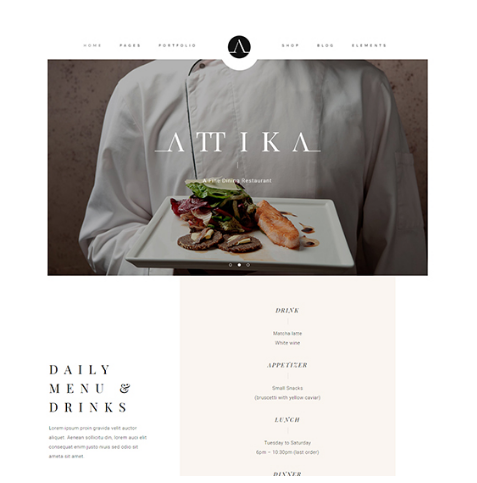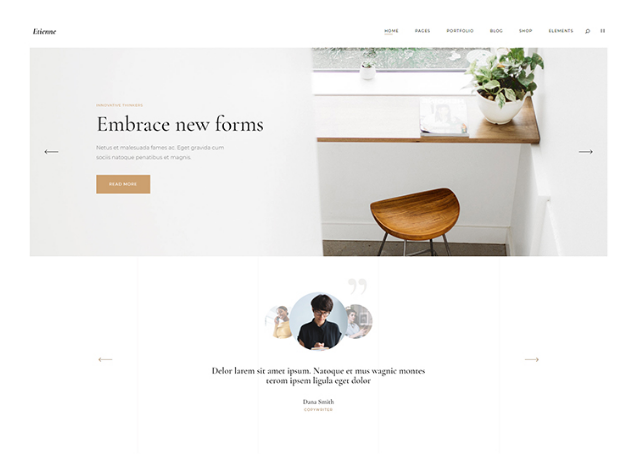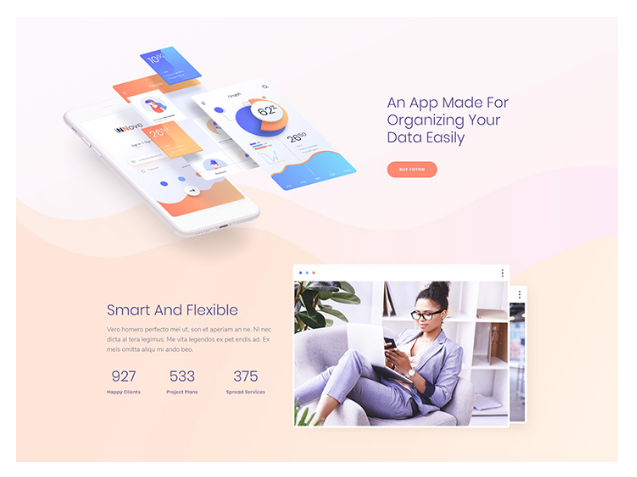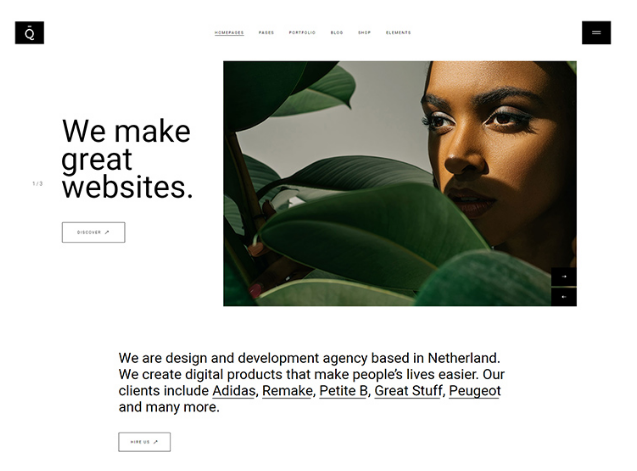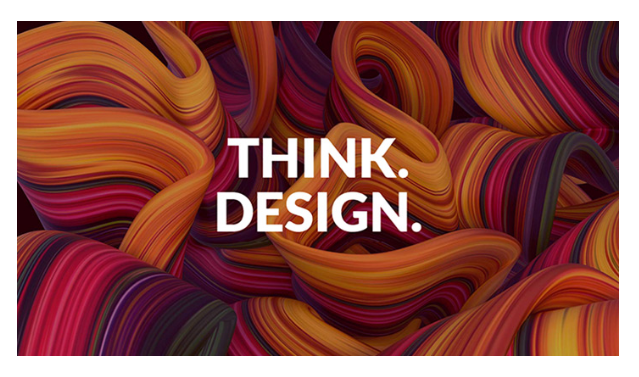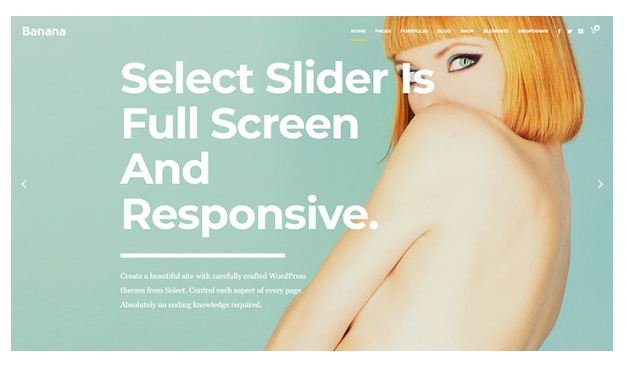
Sito Web di font: cose che dovresti sapere per usare oggi
Pubblicato: 2019-12-19Il sito Web dei caratteri, chiamato anche tipografia, consiste nell'adattare il testo all'interno del design creando al contempo contenuti potenti. Fornisce un aspetto attraente e preserva il valore estetico dei tuoi contenuti. Svolge un ruolo fondamentale nell'impostazione del tono generale del tuo sito Web e garantisce un'esperienza utente eccezionale.
La maggior parte dei visitatori del sito web non si preoccupa molto della grafica, si limita a esaminare il contenuto testuale. Perché i testi sono le principali fonti di informazione. Quindi, mentre crei un contenuto per il tuo sito web, dovresti occuparti di bilanciare la grafica e il testo. È qui che entra in gioco il sito Web dei caratteri. Se sei un web designer, dovresti dare la priorità al sito web dei font.
Perché è così importante?
Un mezzo di comunicazione.
Un sito Web può essere correlato a un'attività commerciale o artistica o a un prodotto specifico. Quando visiti un sito web, puoi facilmente determinare che tipo di informazioni fornisce. Ciò è dovuto all'uso della tipografia.
La disposizione dei contenuti, i colori e i caratteri utilizzati e altri dettagli minuziosi forniscono una via di comunicazione tra il visitatore e il proprietario del sito web.
Attira i visitatori.
L'approccio di base all'utilizzo del sito Web dei caratteri consiste nella selezione del carattere corretto. Il carattere dovrebbe essere il più pulito possibile. Non dovrebbe essere troppo piccolo e scadente. L'uso di caratteri facili da leggere è fondamentale per la presentazione.
I caratteri aggiungono valore al tuo testo. Aiuta i lettori a percepire le informazioni dal testo. La scelta corretta di colore, carattere e dimensione del testo può rivelarsi fondamentale per attirare il pubblico di destinazione.
Trasmette un certo stato d'animo o sentimento.
Un contenuto potrebbe essere una pubblicità di un gioco per computer. Potrebbe contenere alcune interessanti funzionalità del gioco. In tal caso, dovresti progettare il contenuto che sia divertente, giocoso e affascinante.
Se i tuoi contenuti richiedono un po' di serietà, dovresti scegliere caratteri semplici, semplici e professionali. La scelta di tale carattere determina come viene interpretato il contenuto.
Aiuta a stabilire una gerarchia di informazioni.
Gerarchia delle informazioni significa classificare i testi all'interno di un contenuto in base alla loro importanza. Puoi utilizzare diversi tipi e dimensioni dei caratteri per differenziare i testi più importanti.
Puoi evidenziare gli argomenti importanti utilizzando caratteri di dimensioni maggiori. Ciò aiuterà il pubblico a determinare facilmente le informazioni a cui dovrebbe prestare maggiore attenzione.
Aiuta a creare armonia
Se progetti una tipografia e ripeti lo stesso schema durante la presentazione, crea un'armonia. L'armonia è la caratteristica principale nel design tipografico.
Il design armonico fornisce un effetto artistico al tuo sito web. L'utilizzo dello stesso font per contenuti simili fornisce continuità. L'allineamento dei caratteri con le proporzioni corrette organizza la presentazione e la rende ordinata.
Professionalità che riflette.
La corretta aggiunta di font sito web in un progetto di design riflette una grande professionalità. L'uso appropriato del carattere e delle dimensioni del testo guadagna la fiducia dei clienti. Ciò aggiungerà vantaggi alla commercializzazione del tuo prodotto se il tuo sito Web è basato sul business.
L'approccio professionale del design include la tipografia al suo interno. Il sito Web dei caratteri definisce l'importanza dei contenuti forniti e il cliente si sente sicuro riguardo alle informazioni che ottengono.
Crea e crea riconoscimento.
Quando capisci quale design dei caratteri funziona meglio per te, prova a pensare prima allo scopo del tuo design. Una volta determinata la direzione generale in cui vuoi andare, scegli il numero di caratteri tipografici che desideri avere, quindi inizia a navigare sul Web per possibili combinazioni di caratteri. Ci sono molte scelte disponibili, quindi sei obbligato a trovare qualcosa che funzioni bene per te.